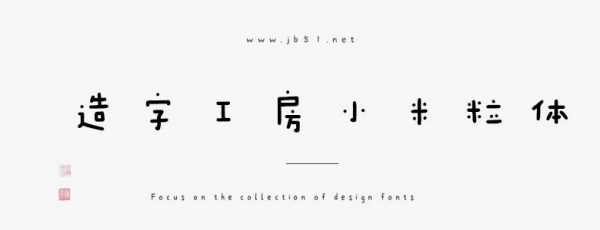
造字工房小米粒體由上首造字字庫(kù)出品的字體,字形靈動(dòng)活潑,大小錯(cuò)落有致,猶如米粒般圓潤(rùn)松散的筆畫(huà)相互堆疊。適合應(yīng)用于平面宣傳設(shè)計(jì)、網(wǎng)頁(yè)設(shè)計(jì),書(shū)法字帖等領(lǐng)域,需要的朋友可以前來(lái)本站下載。
造字工房小米粒體是一款充滿童趣與治愈感的創(chuàng)意字體。其字形靈動(dòng)活潑,大小錯(cuò)落有致,猶如米粒般圓潤(rùn)松散的筆畫(huà)相互堆疊,筆畫(huà)間恰到好處的留白營(yíng)造出米粒滾動(dòng)的輕盈感。整體設(shè)計(jì)充滿動(dòng)態(tài)美感,仿佛躍然紙上的小精靈,特別適合用于營(yíng)造輕松愉悅、溫暖治愈的視覺(jué)氛圍。本字體為簡(jiǎn)體字庫(kù),采用OpenType/CID格式,Adobe-GB1-5編碼。基于中華人民共和國(guó)GB2312-80字符集標(biāo)準(zhǔn),另按需添加101個(gè)漢字。共收容字?jǐn)?shù)6864CJK漢字,ASCII常用字符100個(gè)。